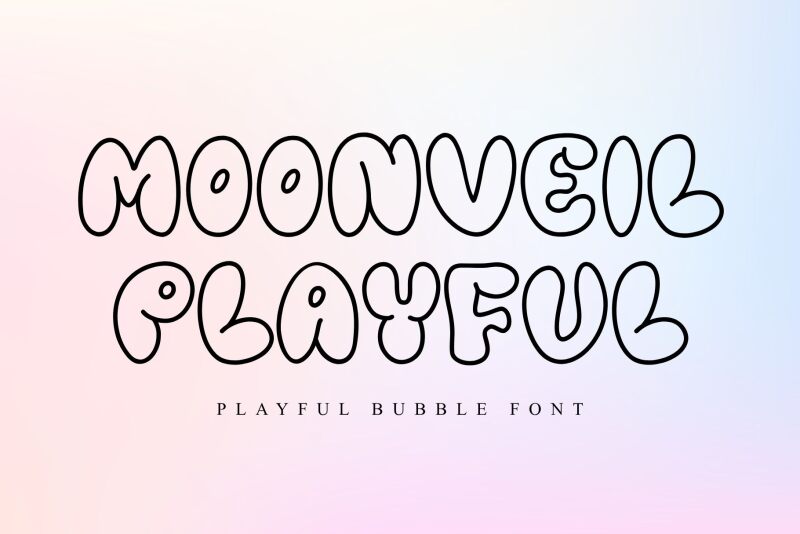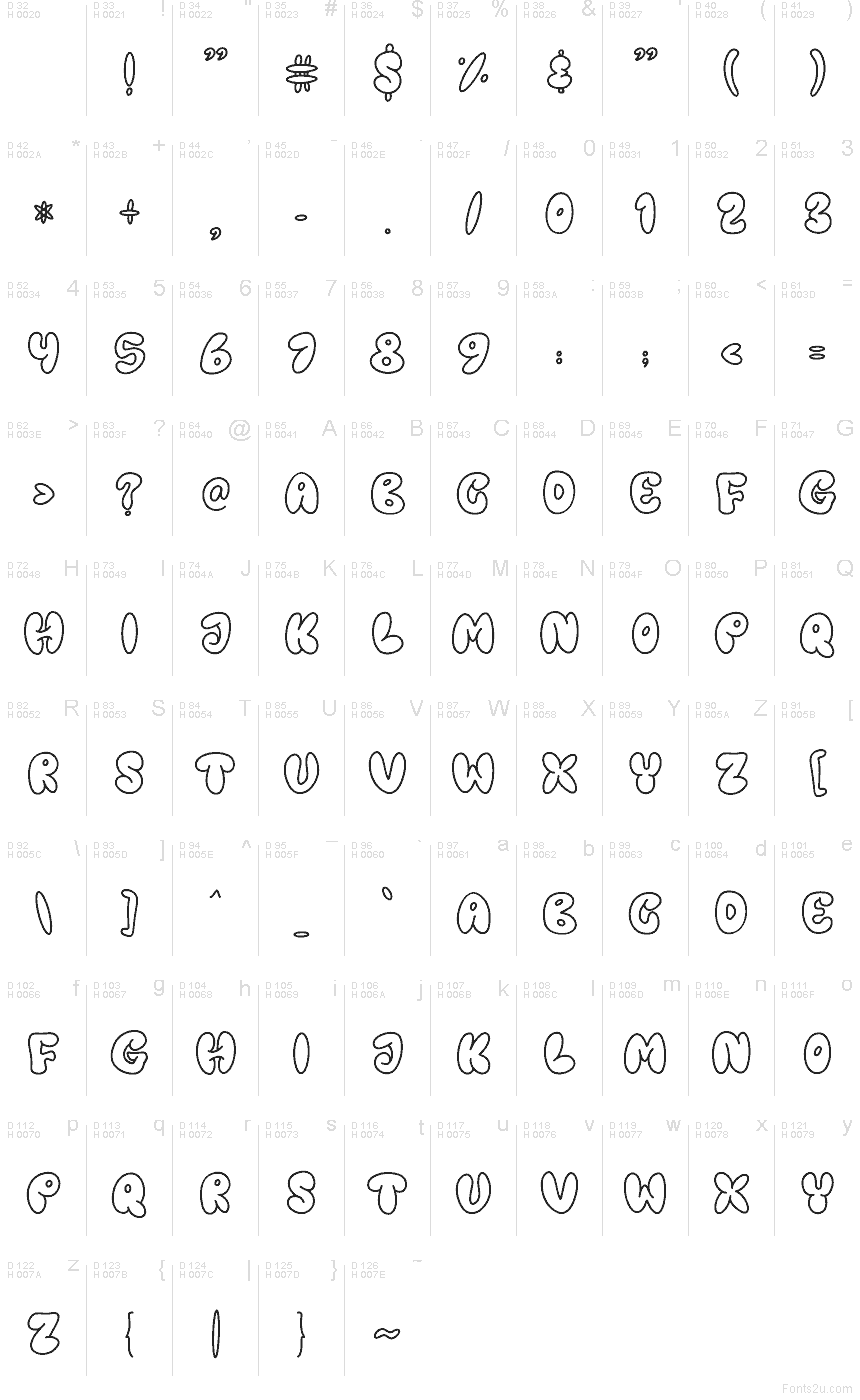
Moonveil Playful od Letterafa je bezplatný obrysový font ve stylu kreslených filmů s měkkým, nafouklým vzhledem. Písmena jsou velká, zaoblená a mírně nepravidelná, díky čemuž font působí spíše hravě než uhlazeně. Díky otevřeným vnitřním tvarům a silným vnějším linkám získávají velká písmena příjemný, ručně kreslený nádech.
Hodí se tam, kde má nadpis působit lehce a dětsky: pozvánky na párty, obaly na svačiny, školní plakáty, komiksové titulky a krátké úvodní obrazovky na YouTube. Jako bezplatný font funguje dobře i pro jednoduchá loga nebo monogramy, zejména pokud chcete, aby obrysy písmena odlehčily, místo aby působila těžkopádně.